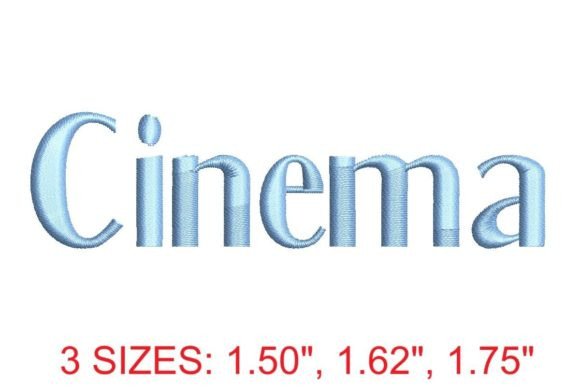
Cinema Embroidery Font
適切なデザイン要素を見つけるのは難しい場合がありますが、Cinema Embroidery Fontは作品を即座に引き立てる優れたコレクションを提供します。
POD(オンデマンド印刷)製品、結婚式の招待状、またはソーシャルメディアのグラフィックを作成している場合でも、Cinema Embroidery Fontは理想的です。